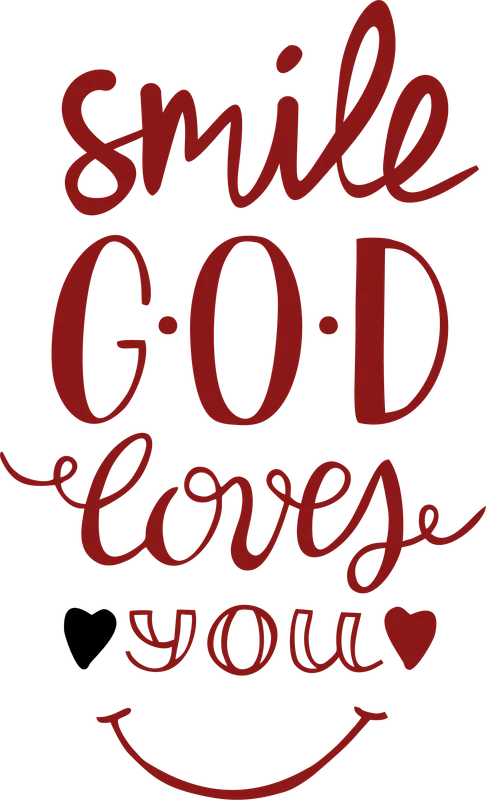
Thông điệp "Smile God Loves You" font chữ nghệ thuật
Thông điệp "Smile God Loves You" font chữ nghệ thuật — Thiết kế chữ "Smile God Loves You" độc đáo, truyền tải thông điệp tích cực. Phù hợp in áo thun, túi tote, sticker. Có thể in chuyển nhiệt.
Trong hình có: chữ viết, trái tim, nụ cười
Phong cách: line-art · Cảm giác: vui
Tông màu chủ đạo: đỏ, đen